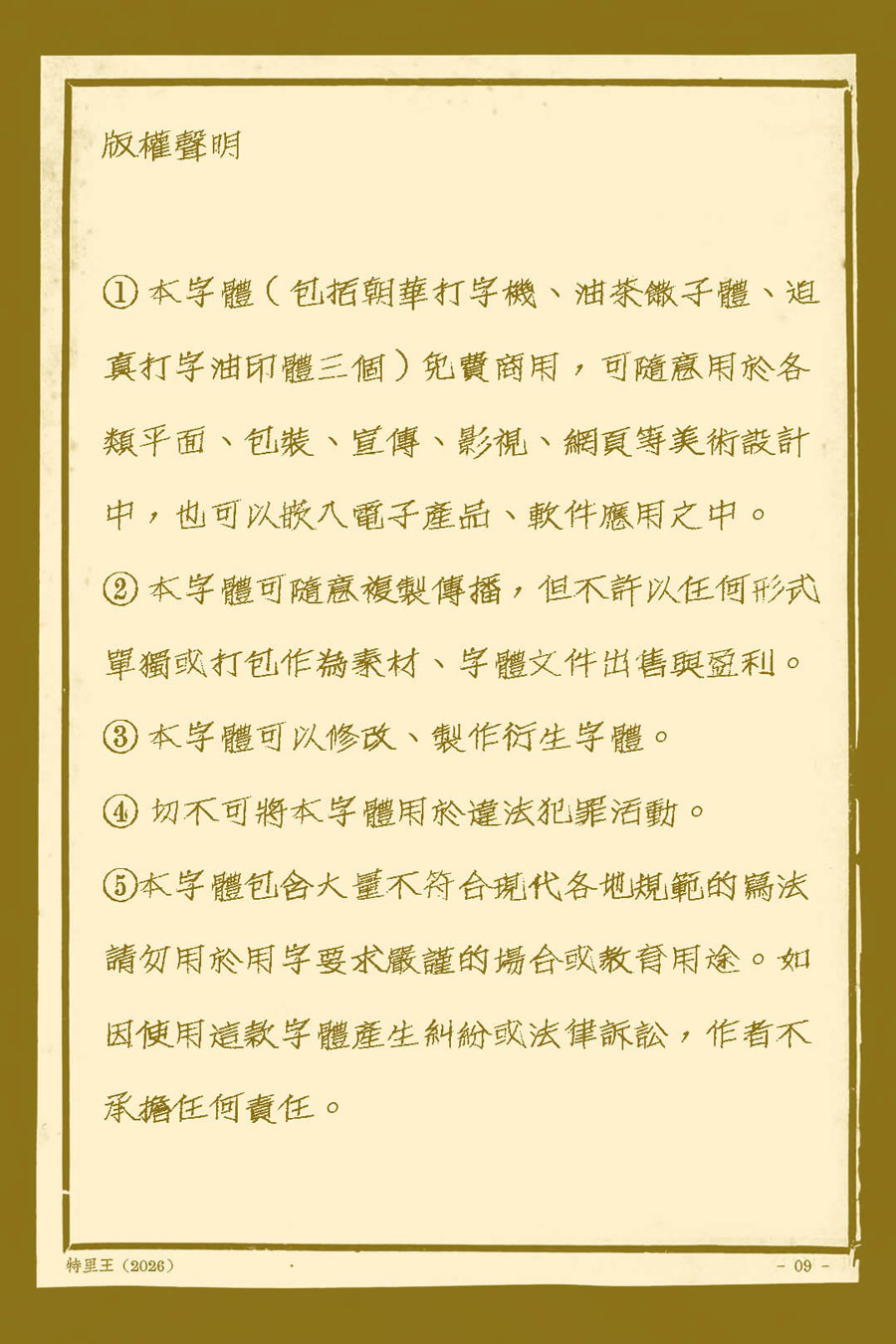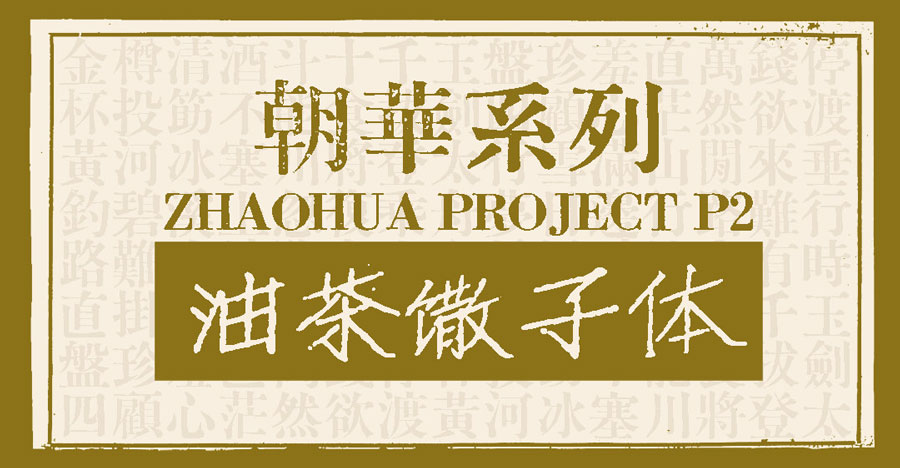
油茶馓子体是由特里王制作的一款免费可商用手写油印字体,是“朝华系列”字体中的一员。由于文字排列出来的效果形似油茶上摊开的馓子,因此得名油茶馓子体。
这款字体模仿老时代手工刻蜡纸、手推油印的味道。字不是工整死板的,笔画线条带有手写抖动、边缘微糊、油墨深浅不匀,满满的复古旧纸张质感。尤其适合需要营造复古氛围或手写风格的设计项目,比如老海报、民国风广告、怀旧文创和文艺手账等。